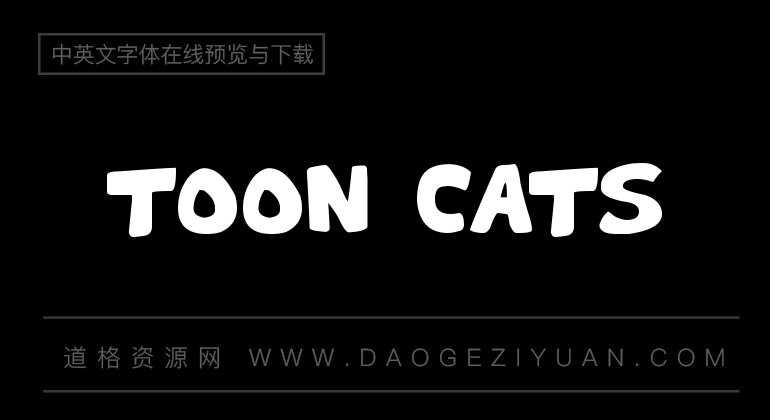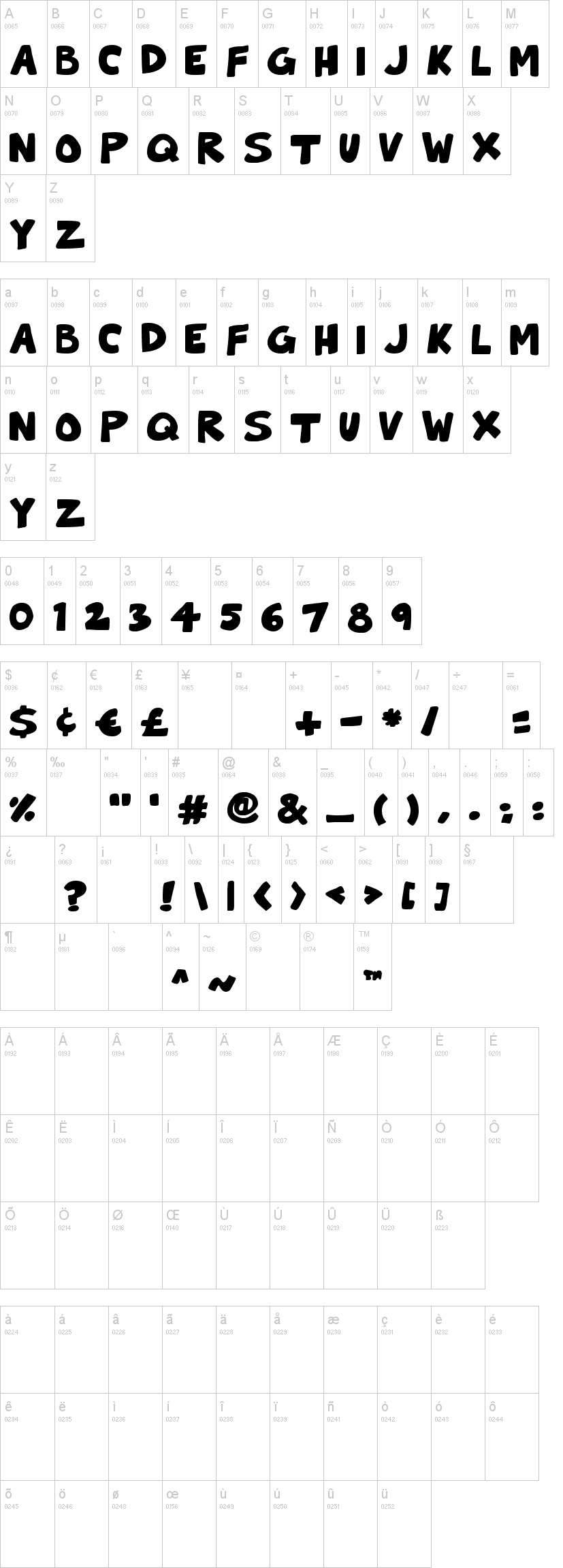
吧? Toon Cats 是一种漫画风格的字体,它采用了非常有趣的笔画,使用它可以让文字看起来更有趣,更有表现力。它适用于各种年龄段的人,可以用于多种场景,如海报、书籍、漫画、游戏等。Toon Cats 字体的特点是它的自然线条,有着流畅的曲线,使文字看起来更加生动有趣。它的笔画比较粗,有着独特的风格,可以让文字看起来更加有趣,更有表现力。内容介绍
Toon Cats是一款非常不错的手写艺术字体,具有很好的视觉感,适合于文化类的宣传设计、商业类品牌的广告和产品包装设计以及个性化文字排版等较多场景。